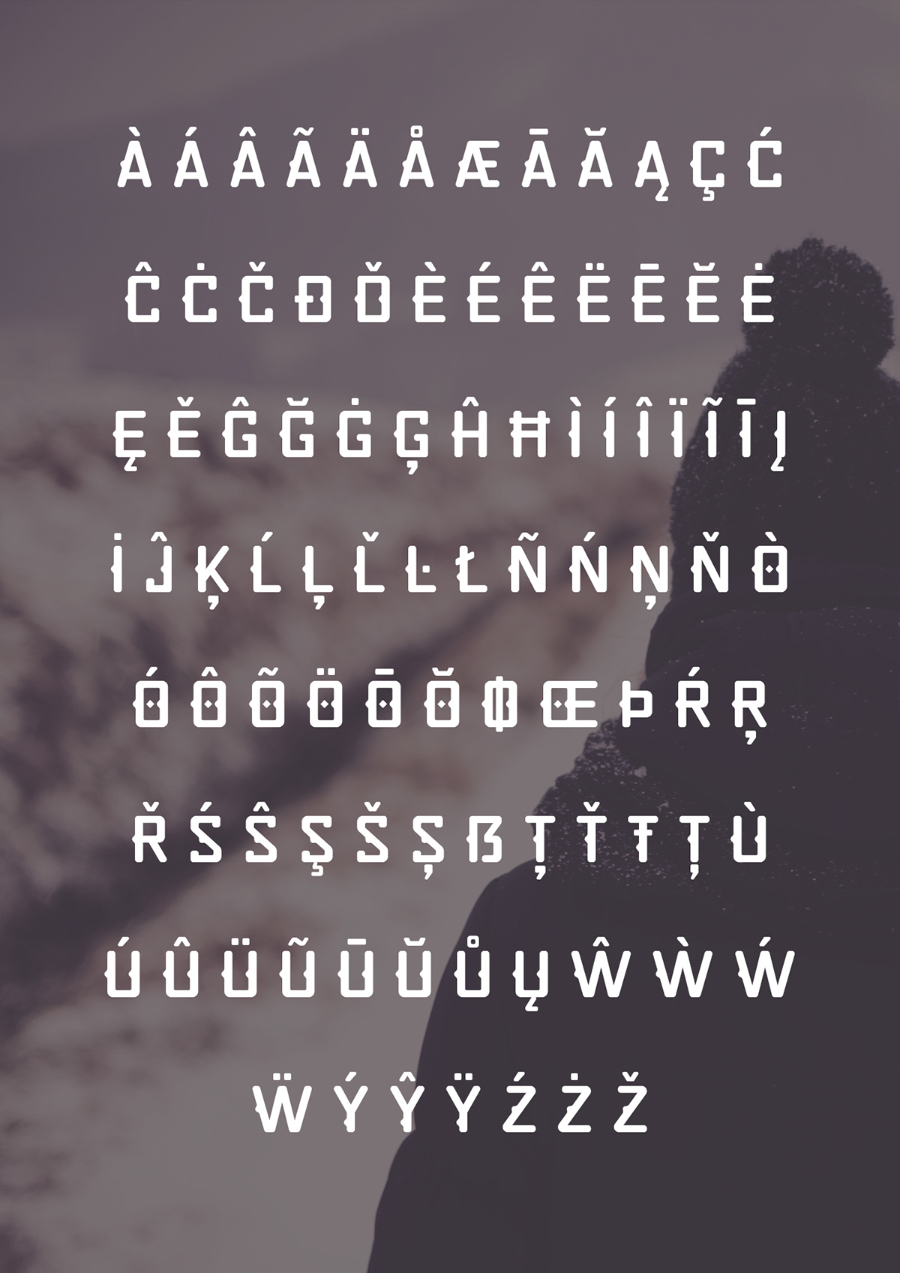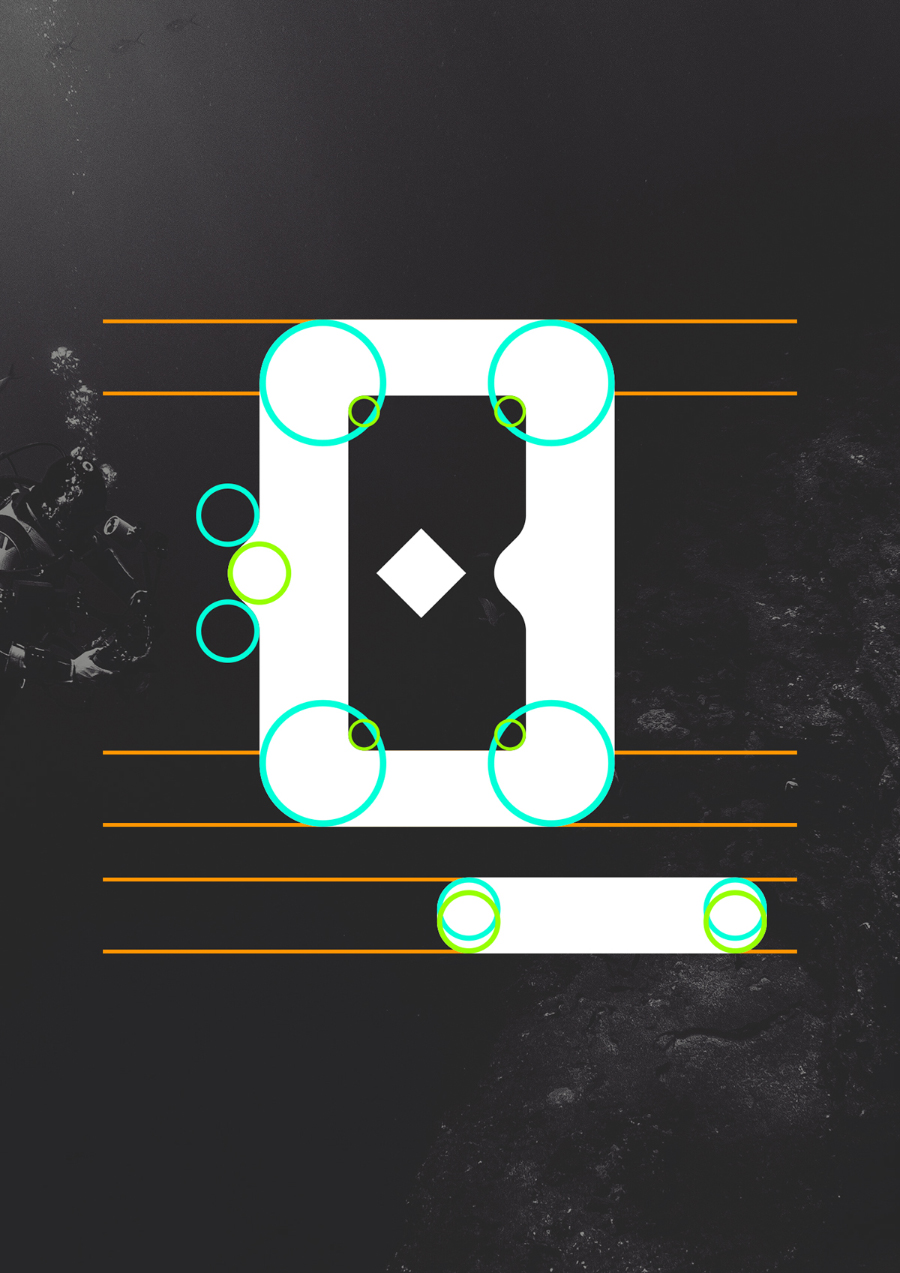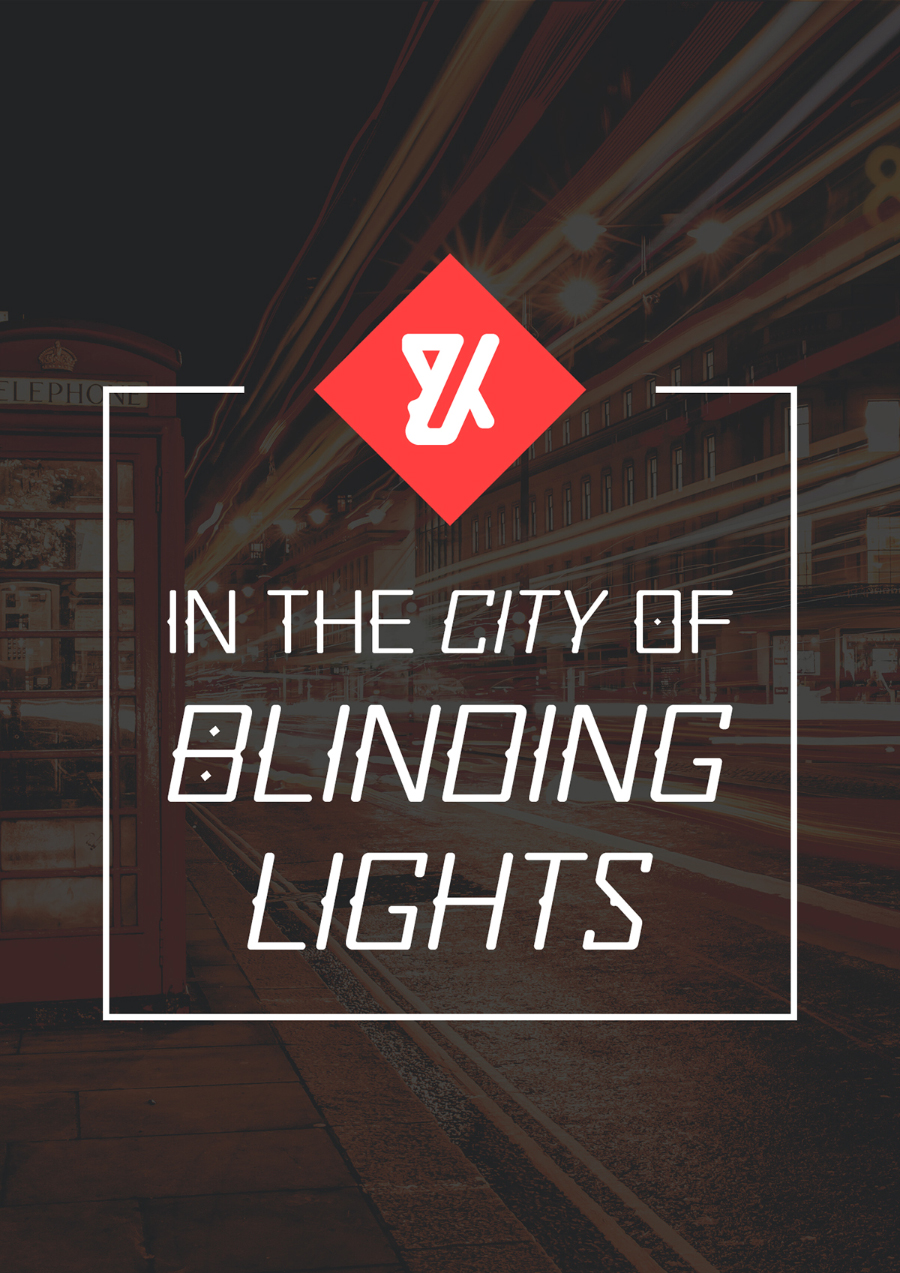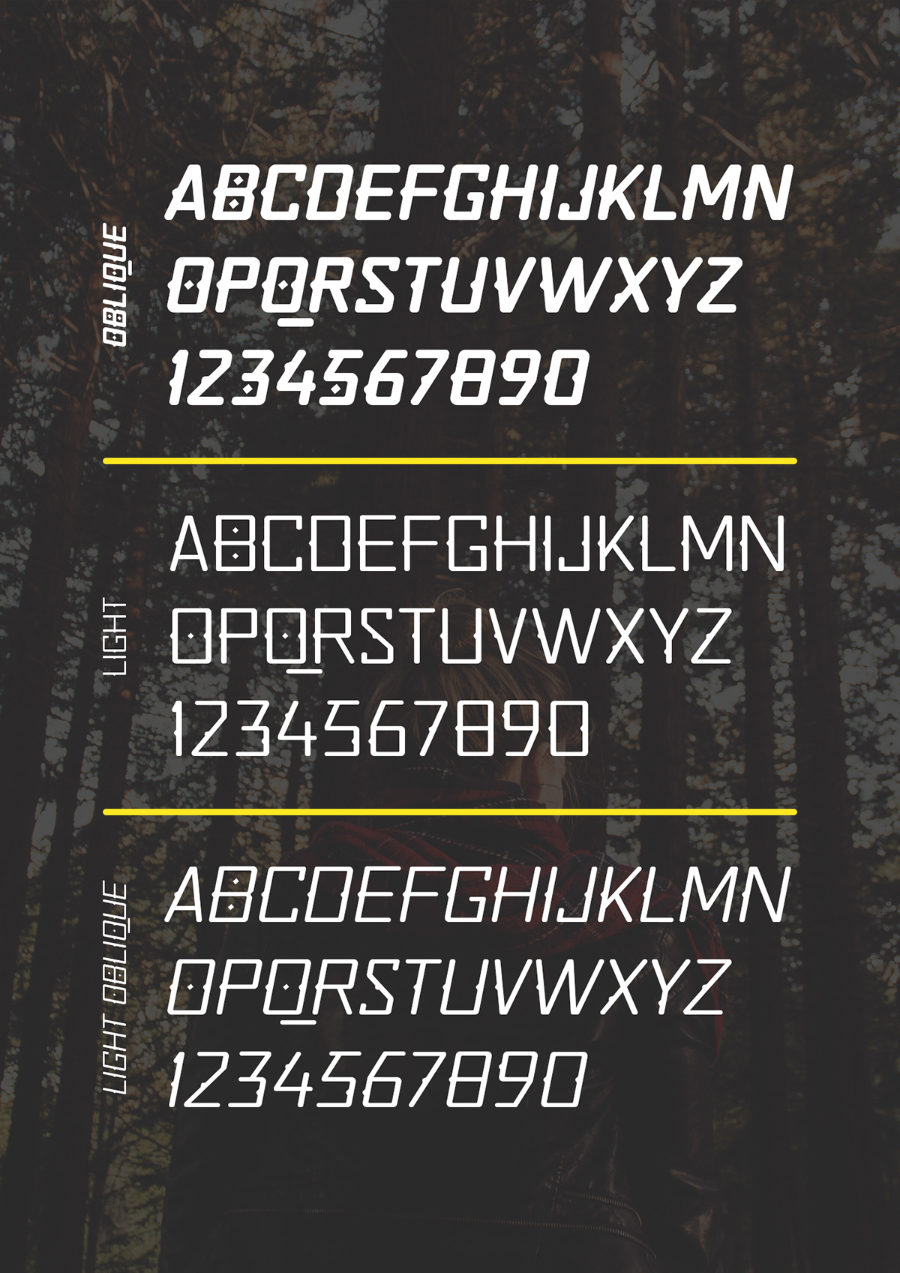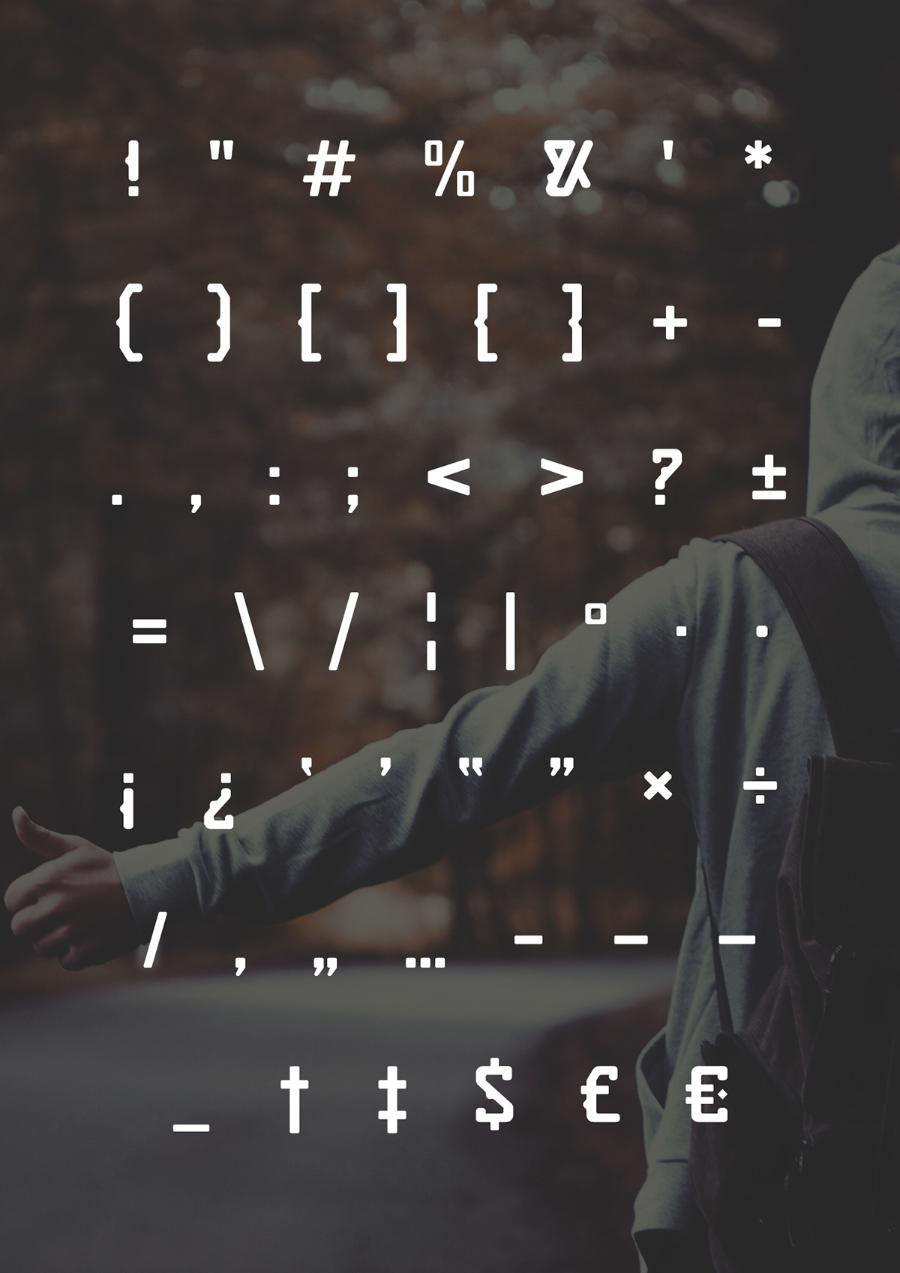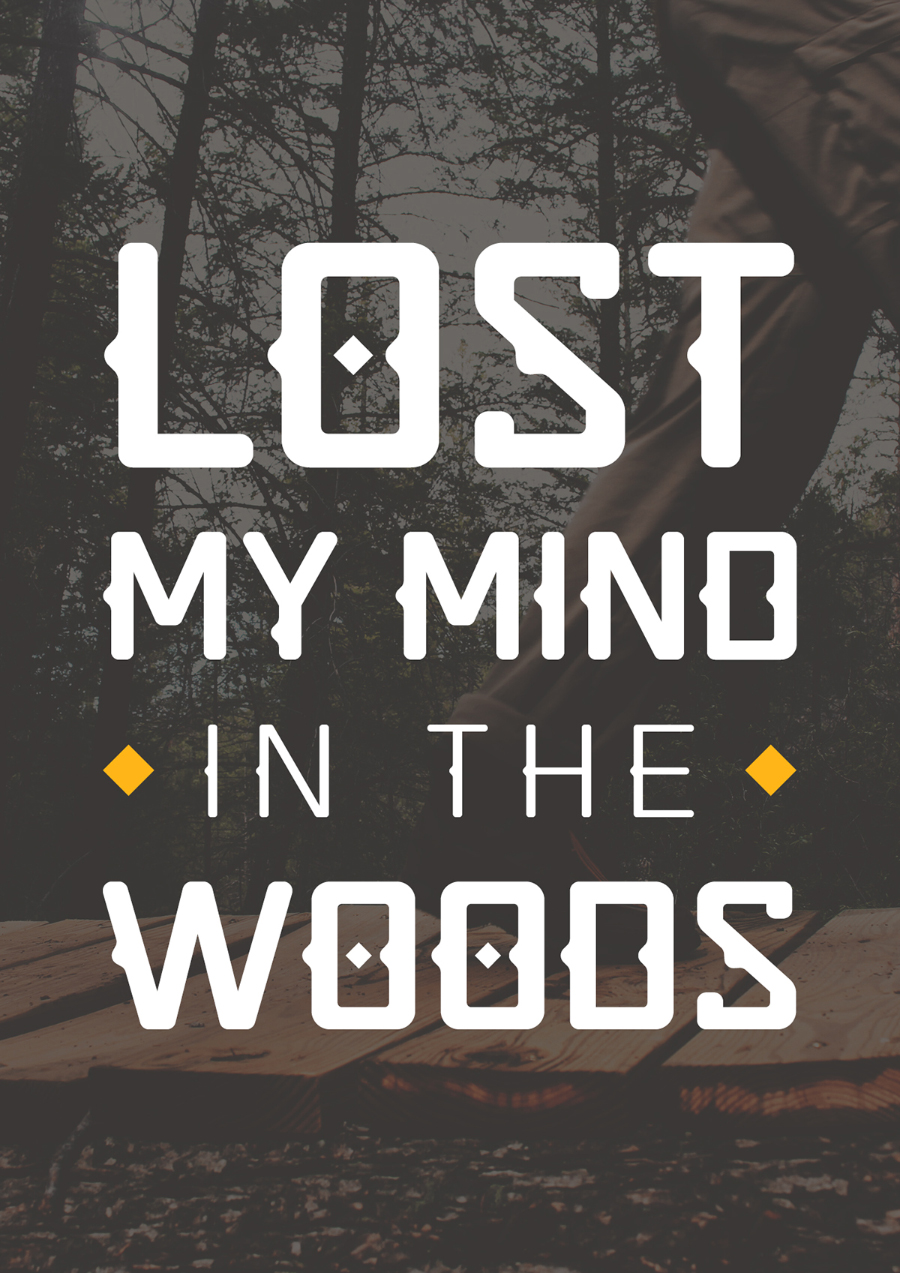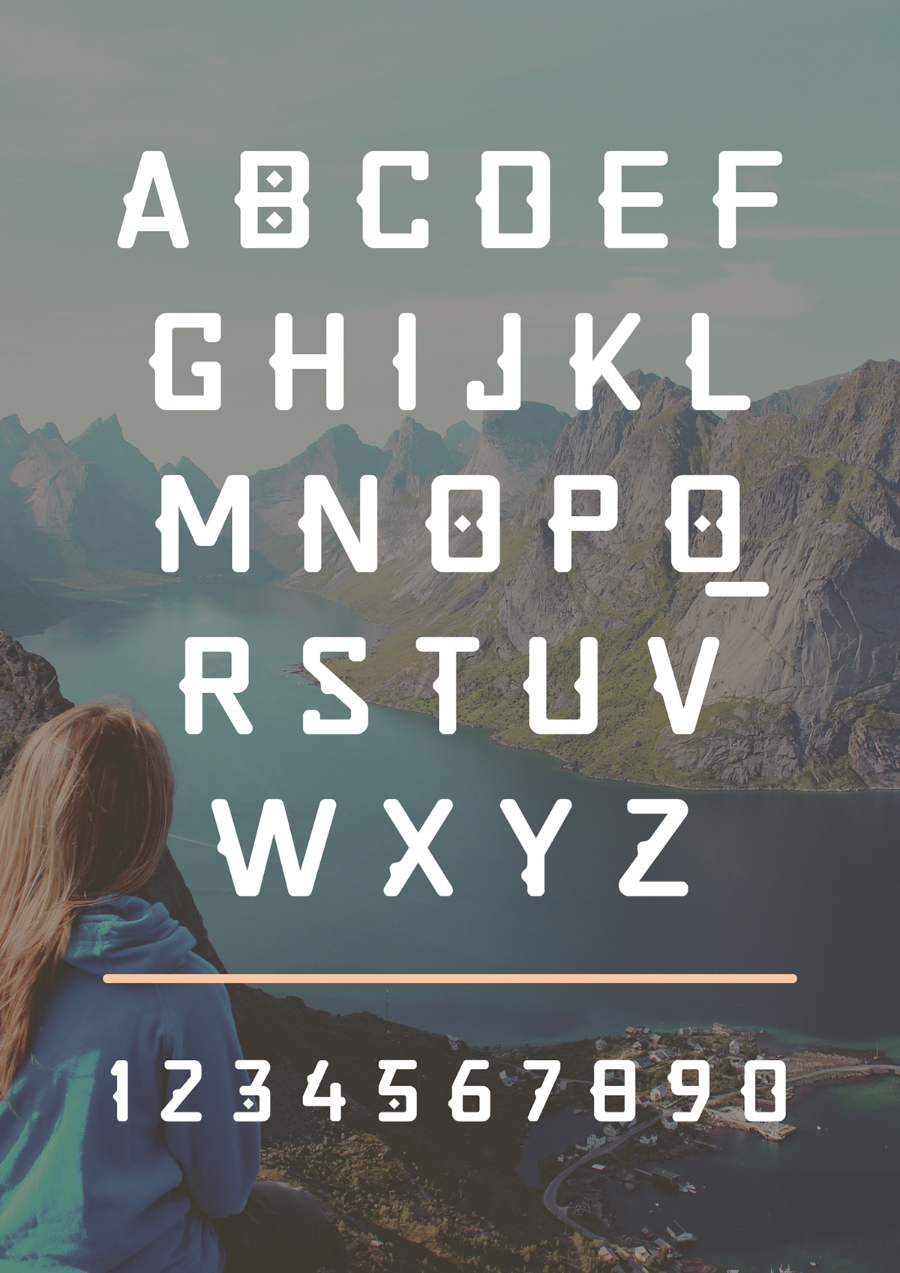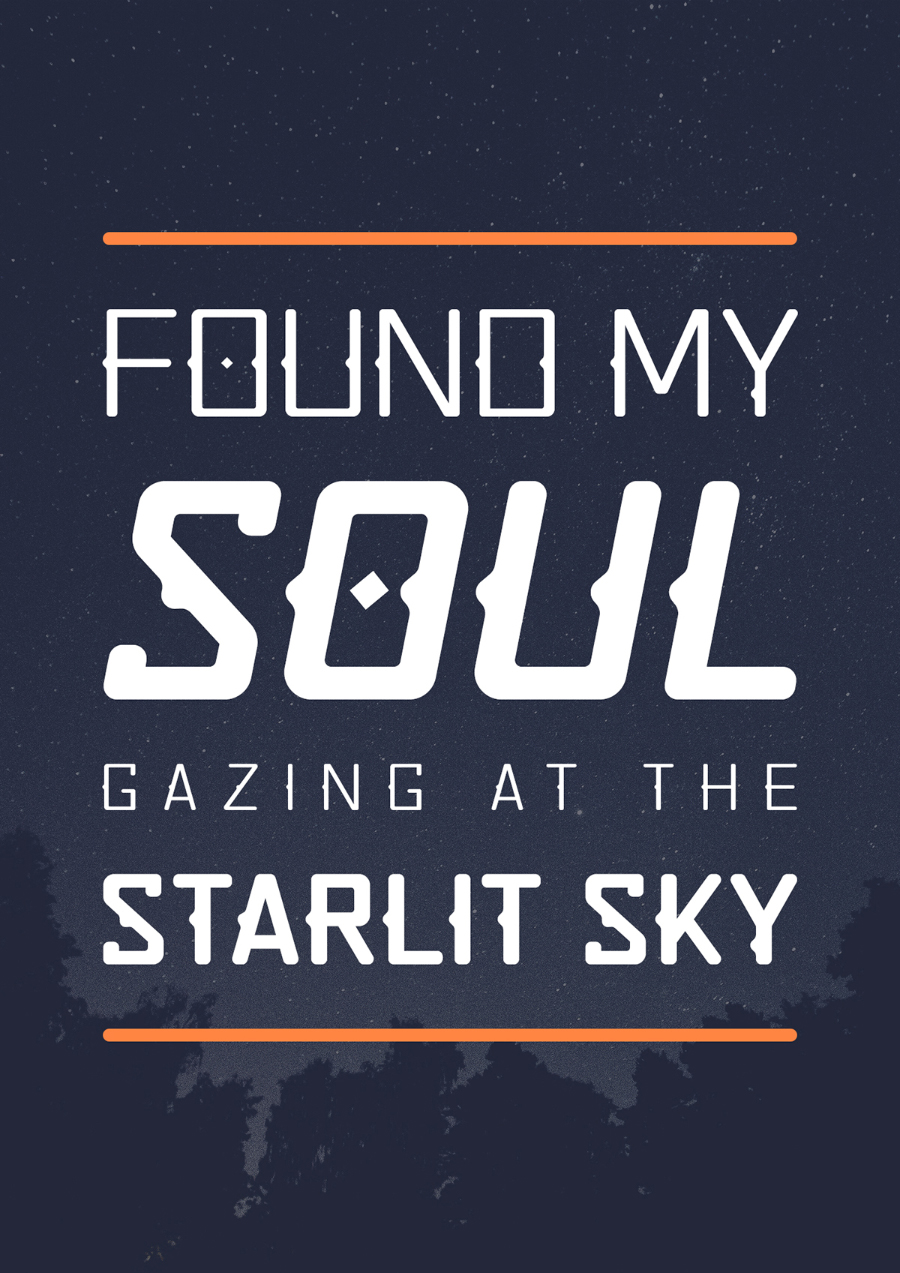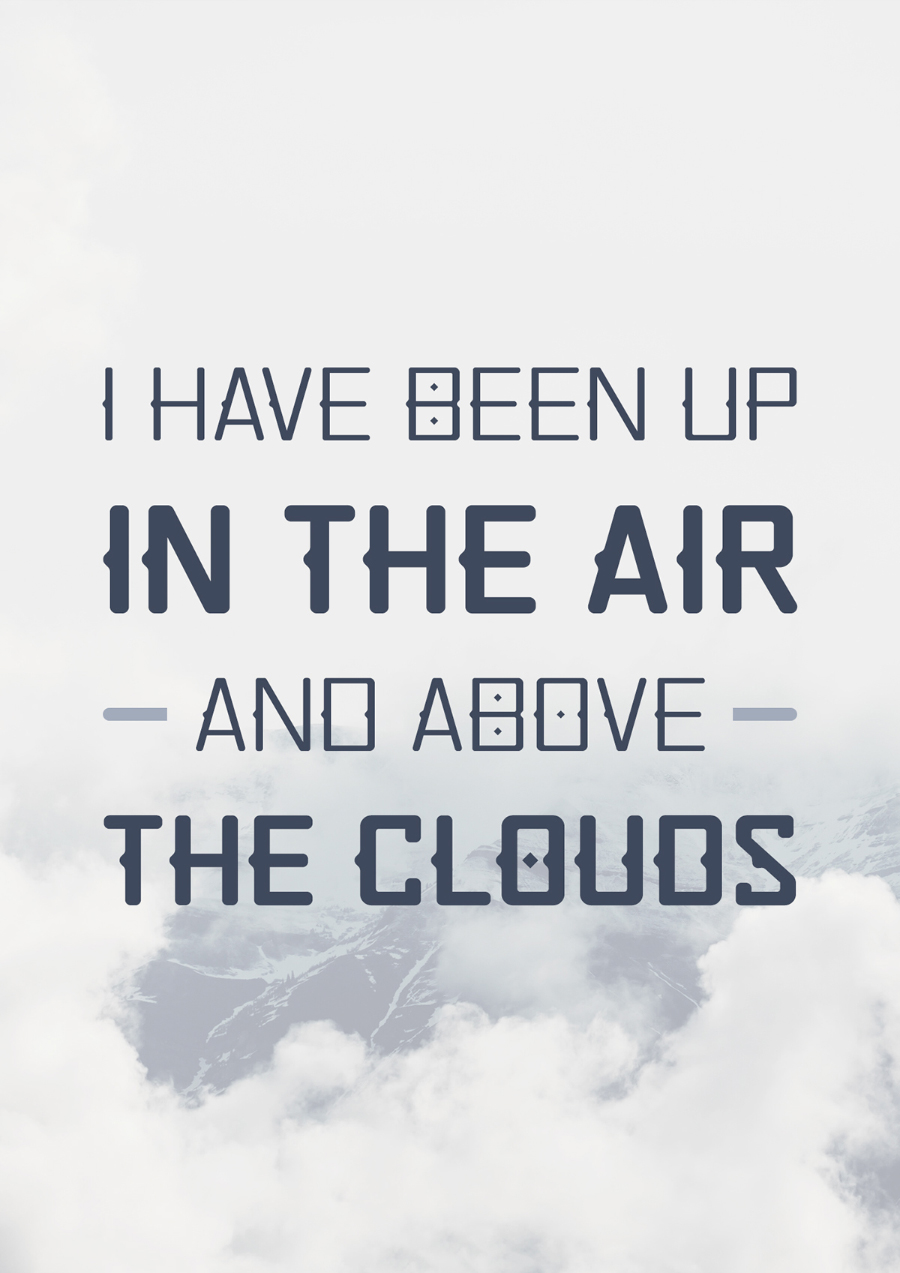
Quirko显示免费字体
Quirko Display Free Typeface
Quirko显示免费字体是由高,圆形的无衬线字体启发的4种字体家族。某些字形中的菱形元素的圆形三角形凸起给字体赋予了偏心的美感。这与其自信的外观和多重重量相结合,使Quirko适合数字和印刷媒体的字体。每个字体包含300多个字形。因此,Quirko在标题,标识,品牌和广告方面看起来也很棒。